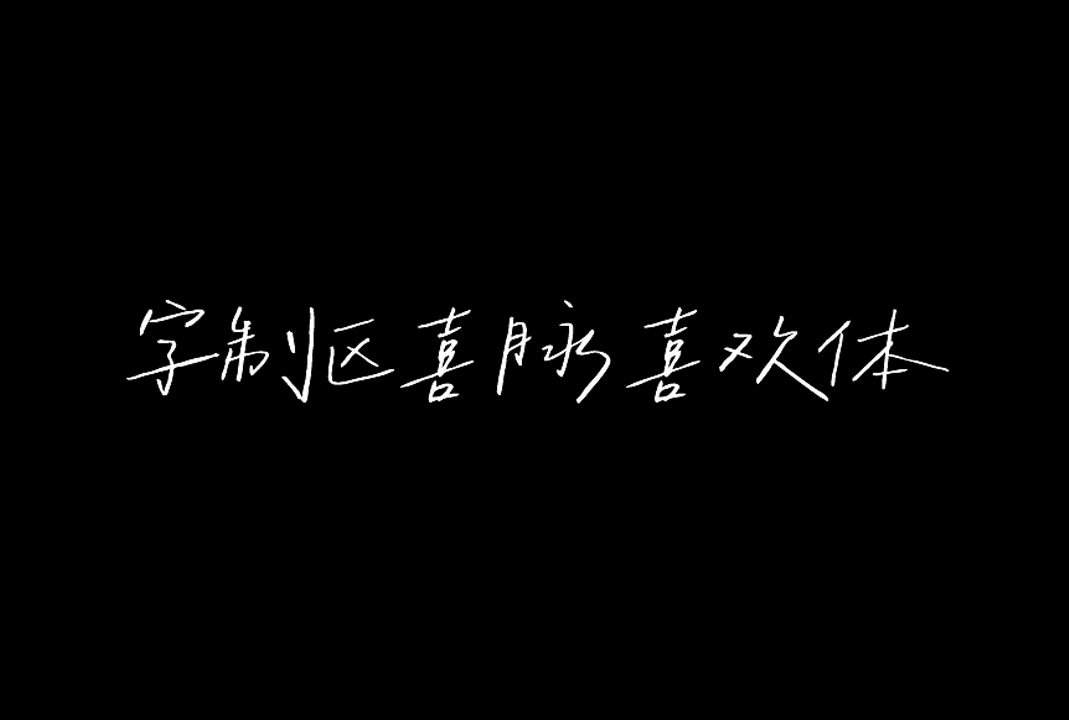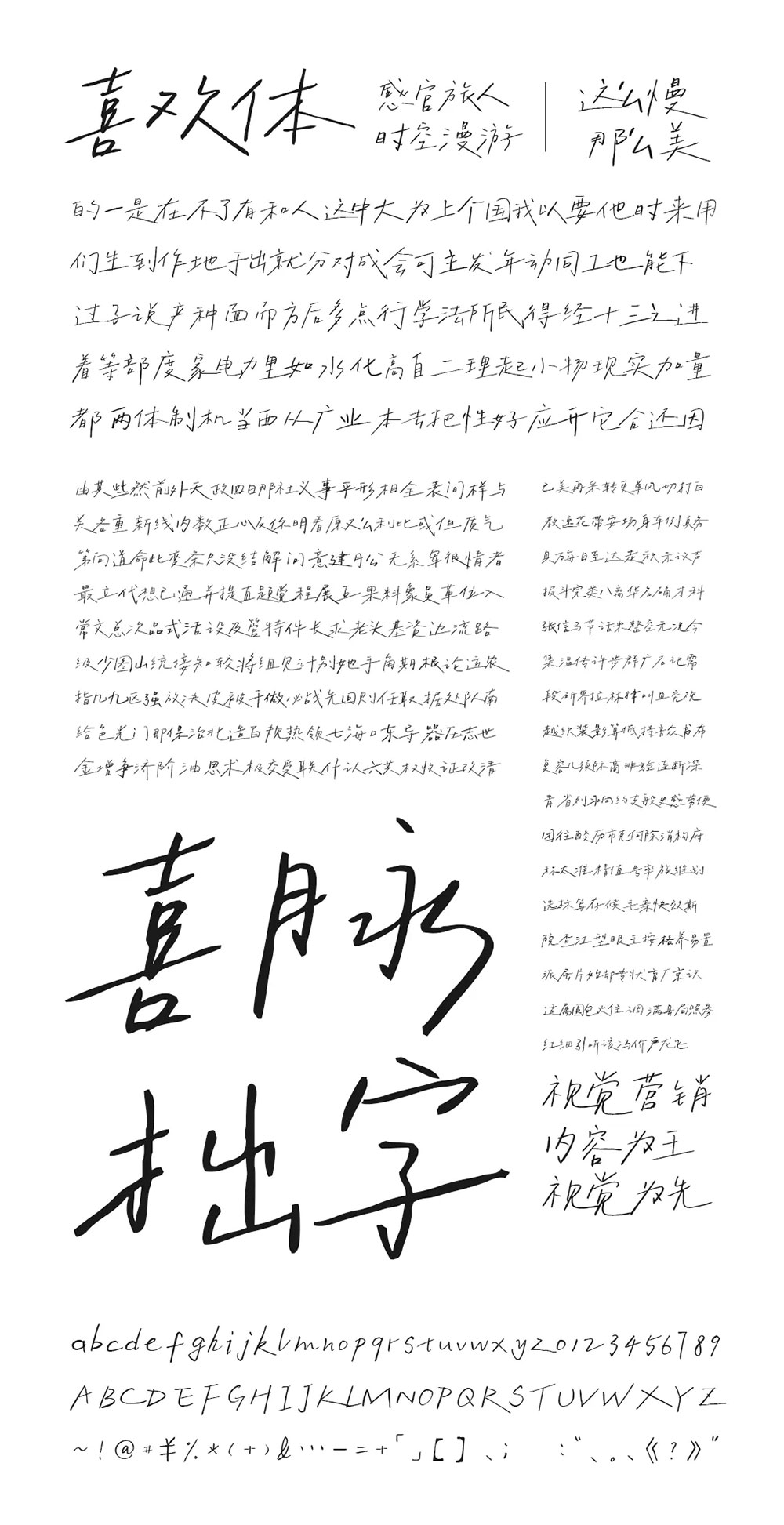
字制区喜脉喜欢体(FontQu Smile 常规)是由字制区(微信公众号:FontQu)于2024年发布的一款手写风格字体;
字制区喜脉喜欢体(FontQu Smile 常规)是一款简体中文字体,字体总字数: 7367,英文: 104,数字: 93,标点: 67,符号: 44,涵盖了日常所有常用字符。
字制区喜脉喜欢体(FontQu Smile 常规)风格清馨、文艺、自由,比较适合作为字数少的大标题使用,如自媒体封面标题/字幕、音乐专辑、电影海报、杂志、照片排版等场景。